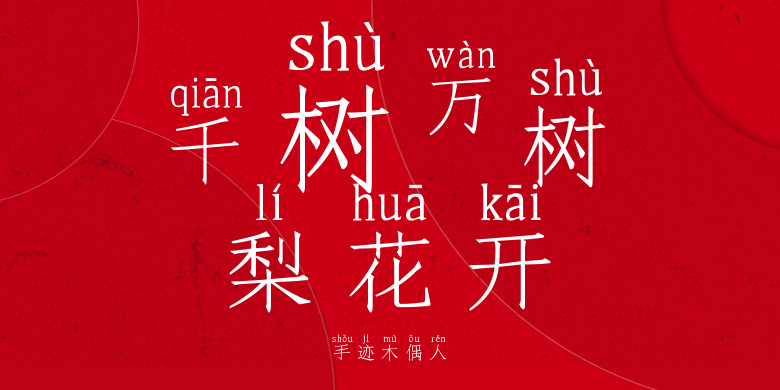
手迹木偶人
手迹木偶人,这款字体结构工整、笔画清晰,兼顾美观与易读性,适用于标题、正文、海报、包装、LOGO 等多种场景。字形优雅稳定,风格百搭耐看,适配日常排版与创意设计,让文字呈现更舒适、更具质感。手迹木偶人一笔一画,皆是细节,以均衡的比例、流畅的线条打造舒适视觉体验,字形端正大气,风格简约现代。无论是商业设计、品牌宣传还是日常排版,都能轻松驾驭,让文字更有格调与力量。手迹木偶人字体下载。